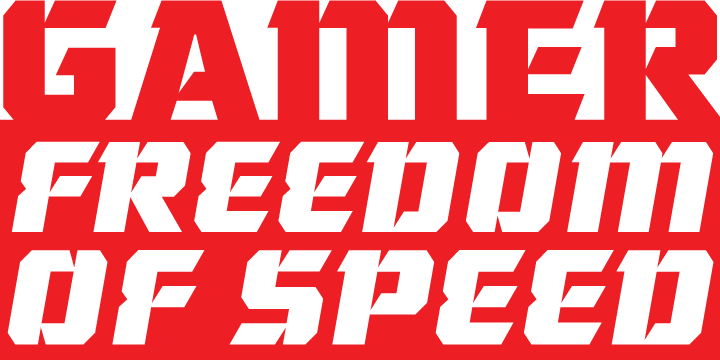
В данном архиве шрифты со следующих популярных игры:
— СounterStrike
— The Elder Scrolls V: Skyrim
— Fallout
— Grand Theft Auto San Andreas
— Need for Speed: Most Wanted
— Need for Speed: ProStreet
-stalker
— The Sims 3
— World of Warcraft
— Watch Dogs